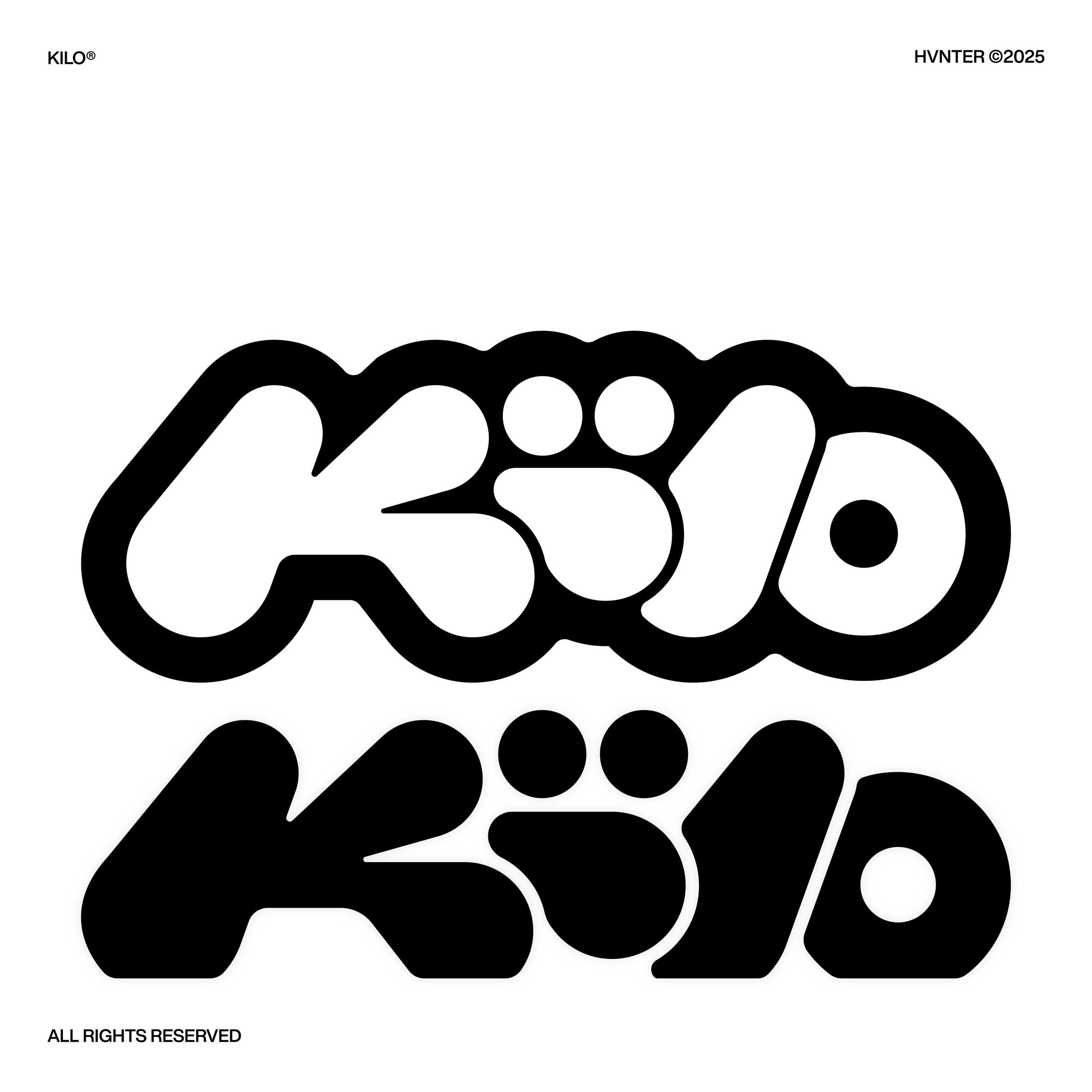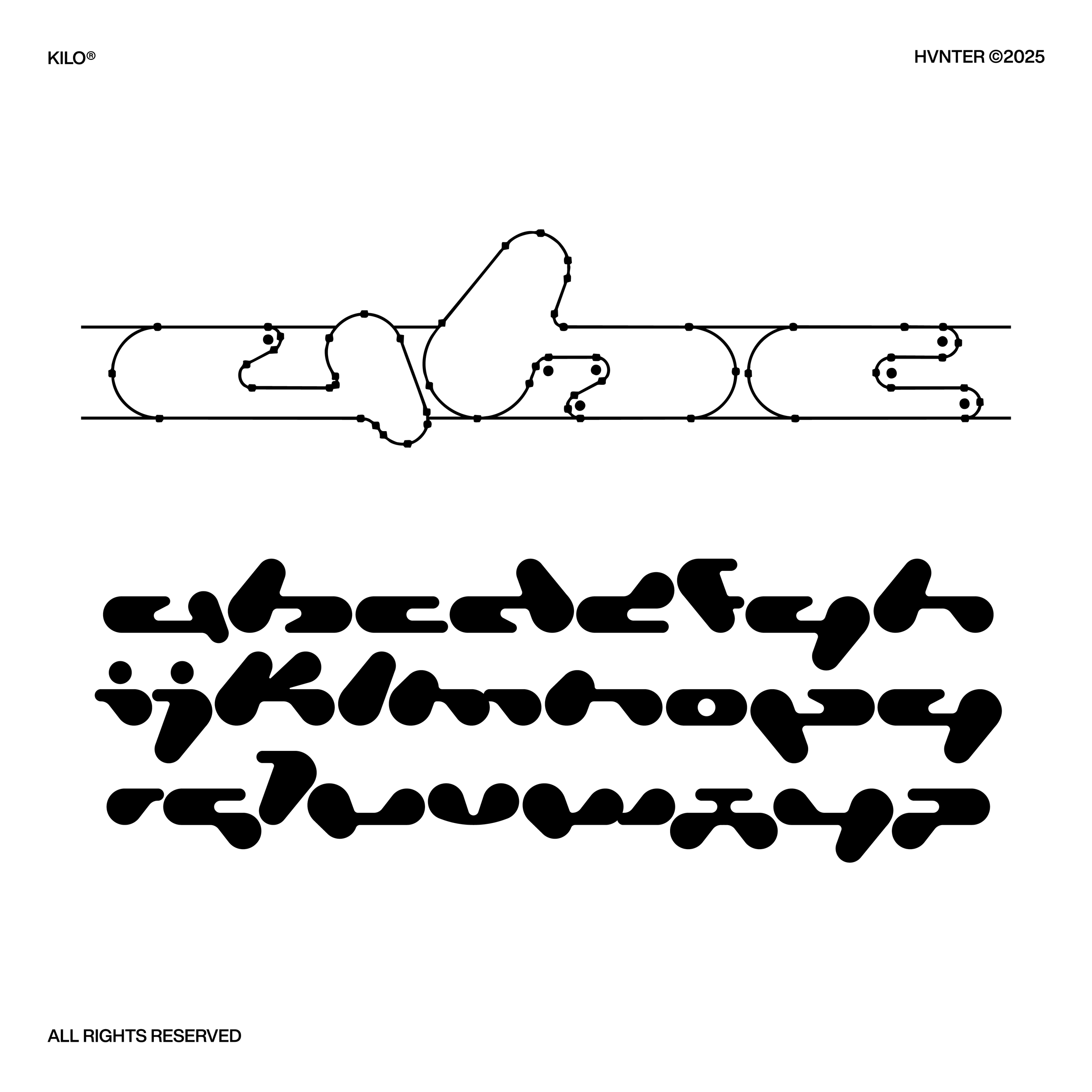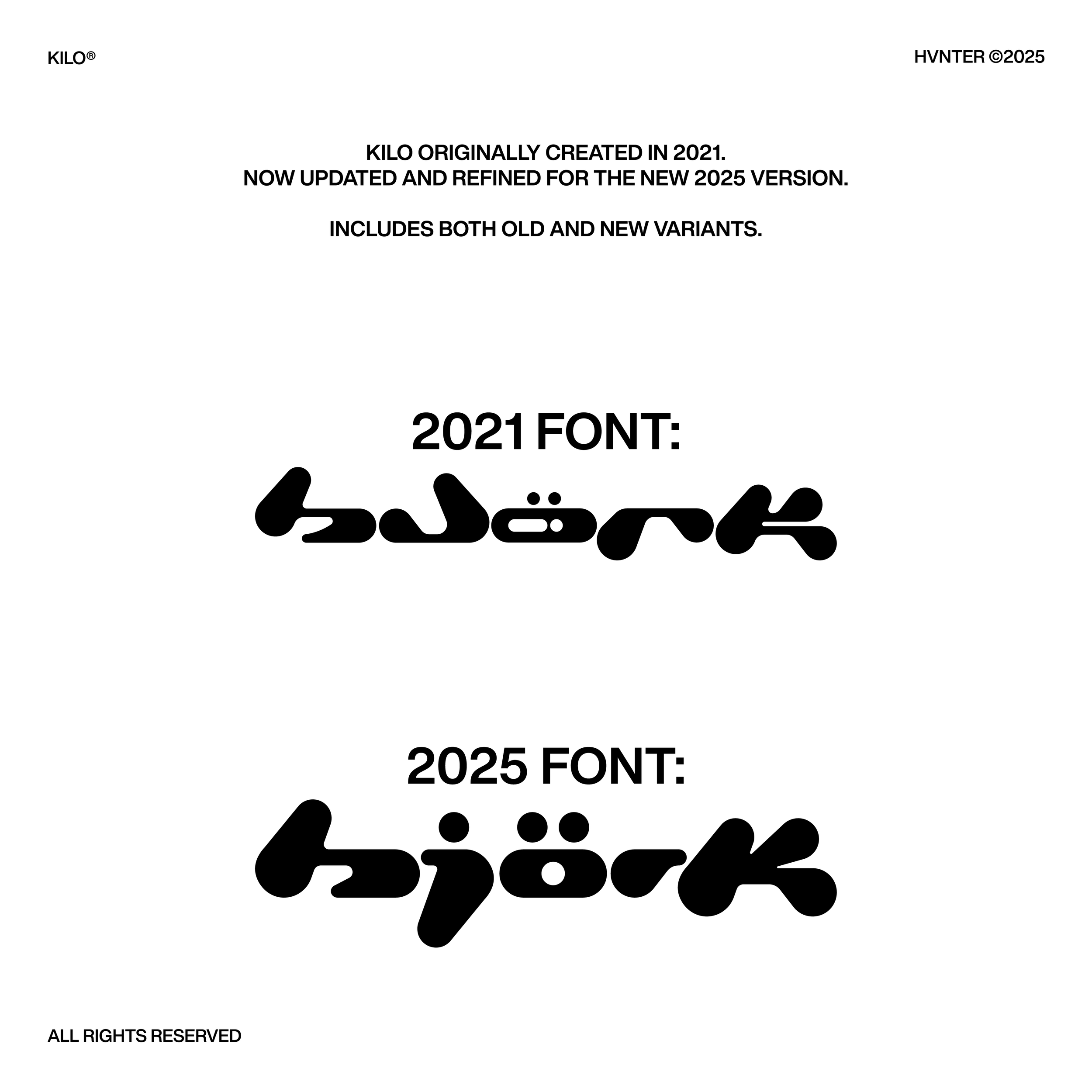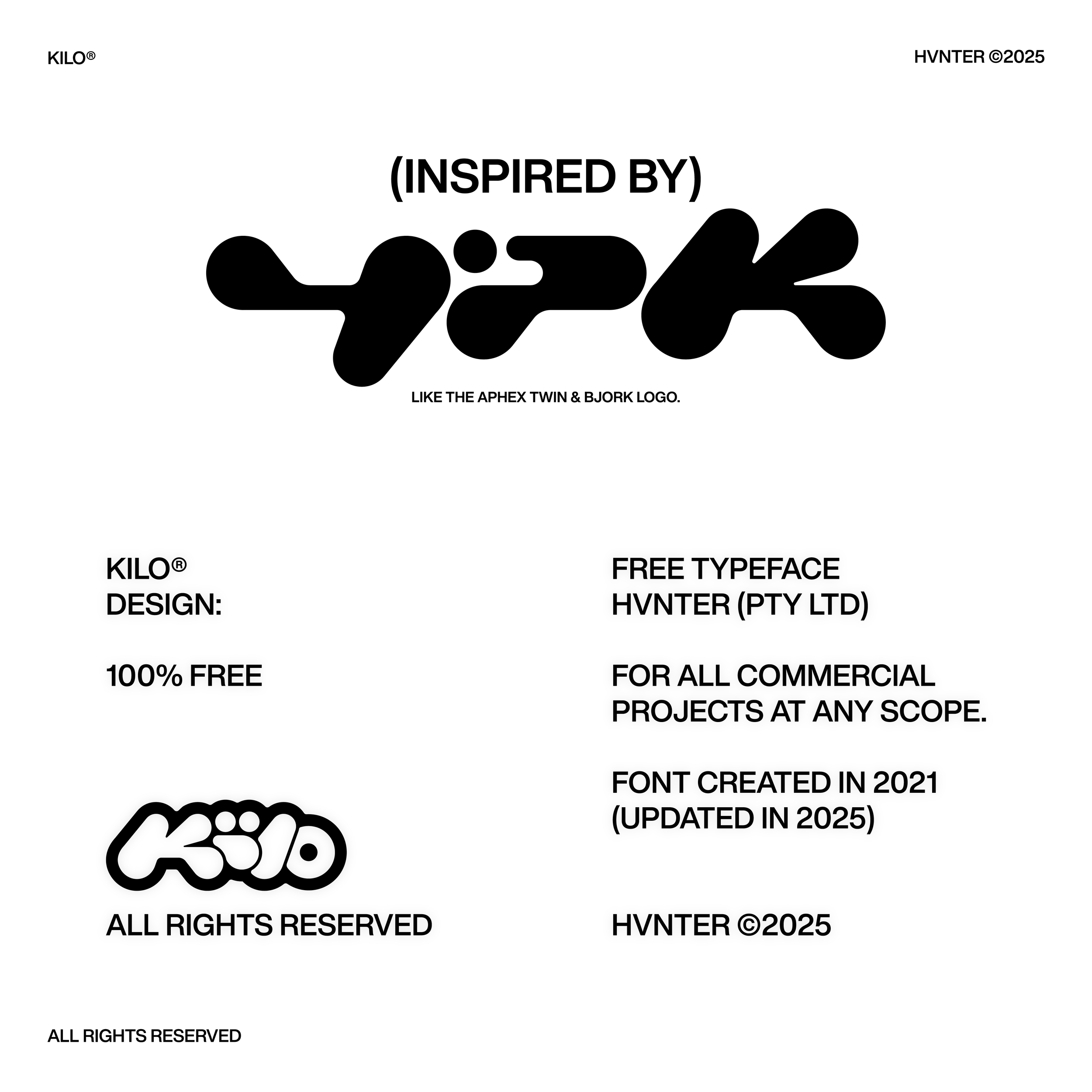
Kilo
在复古未来主义视觉重新受到设计领域关注的当下,Y2K风格字体也逐渐成为品牌视觉、海报设计和数字媒体中颇具辨识度的一类字体。由Hvnter设计的Kilo Typeface,正是一款具有鲜明Y2K视觉特征的展示字体。设计者将厚重的字形结构与圆润、流动的曲线结合,使字体在保持强烈视觉重量的同时,又呈现出一种带有数字时代气息的轻松与趣味。
从整体字形来看,Kilo并没有采用传统几何字体规整、统一的构造方式,而是通过大量圆角、弧线以及不规则转折重新组织字母结构。部分笔画之间具有明显的连接感,使单个字符看起来更像经过压缩和拉伸后的视觉符号。这种处理方式弱化了传统西文字体中严谨的骨架关系,让Kilo拥有更加鲜明的图形化特征。
Kilo最具辨识度的特点之一,是其厚重而柔软的视觉轮廓。粗壮的笔画配合圆角端点,让字体整体呈现出类似气泡、软体几何或数字图形的视觉效果。相比普通粗体字体,Kilo并不是单纯增加笔画重量,而是通过轮廓变化改变字符的整体比例,因此即使在较大的字号下使用,也能够保持独特的造型感。
这种设计语言与Y2K美学中常见的未来感、数字感和实验性视觉具有较高契合度。字体既能够体现早期数字产品和互联网视觉中的复古气息,也能够融入如今更加流行的潮流品牌、音乐视觉和年轻化设计体系。因此,Kilo并不适合作为大段正文使用,而更适合承担标题、标志、短句和视觉主体文字等需要强调识别度的设计任务。
值得注意的是,Kilo并不是只有一个版本。根据设计者Hvnter发布的信息,该字体最初创作于2021年,并在后续进行了更新,2025版本是在原有设计基础上的重新调整与优化,同时保留了原始版本。 从展示图可以看到,两个版本在整体视觉方向上保持一致,但2025版本的字形关系更加完整,部分字符的轮廓、比例和细节进行了重新处理,使新版在视觉展示时具有更加成熟统一的效果。
从设计应用角度来看,Kilo尤其适合需要突出个性与视觉冲击力的场景。例如在潮流品牌Logo、服装与鞋类视觉、音乐海报、活动标题、游戏视觉、社交媒体封面、包装设计以及数字产品宣传图中,可以利用其厚重的字形快速建立视觉焦点。对于较短的英文单词或品牌名称而言,Kilo的字形本身就具有较强的图形属性,即使不搭配复杂的装饰元素,也能够形成具有辨识度的版式效果。
在排版使用时,Kilo更适合采用较大的字号进行展示,并通过留白、字距和背景对比进一步强化字体轮廓。由于其字符本身具有较强的造型特征,如果文字内容过长或者字号过小,复杂的字形关系反而容易降低阅读效率。因此,在实际设计中可以将Kilo定位为视觉标题字体或装饰性展示字体,再搭配简洁的无衬线字体完成正文信息,从而形成更加清晰的层级关系。
总体而言,Kilo是一款具有鲜明个性的Y2K展示字体。它没有沿用传统字体追求高度规整的设计思路,而是通过圆润轮廓、厚重笔画和富有流动感的字形结构,将文字进一步转化为具有视觉表现力的图形元素。2025版本在延续原版设计语言的同时进行了进一步优化,使这款字体能够更好地适应当下的潮流品牌、数字视觉和创意设计需求。对于正在寻找Y2K字体、未来感英文字体、圆润展示字体以及个性化标题字体的设计师而言,Kilo是一个值得关注的字体选择。